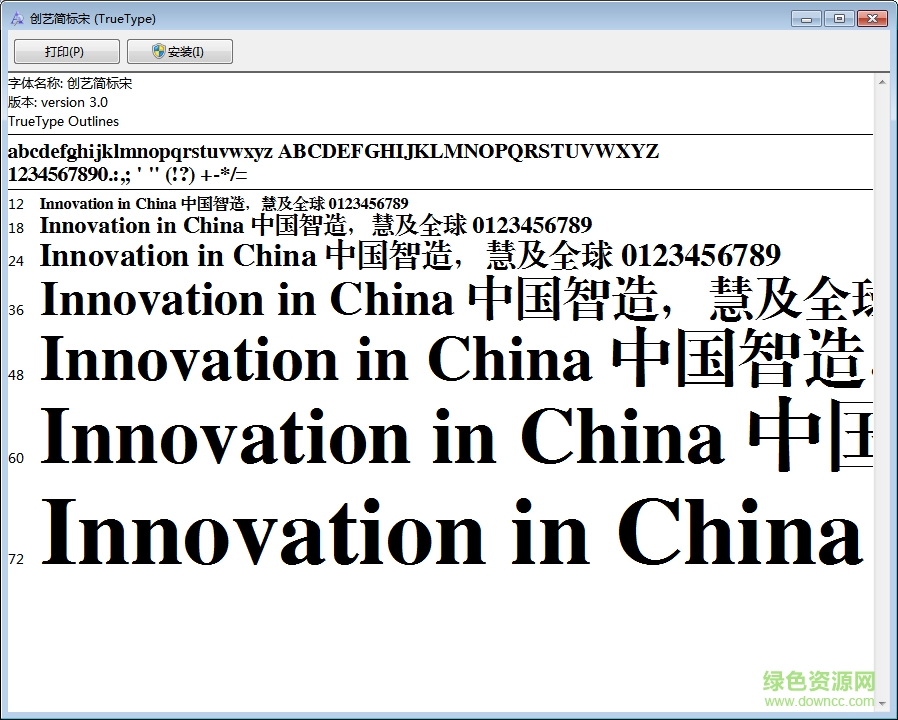
ctbiaosongsj 是什么字體?ctbiaosongsj.ttf字體又叫創(chuàng)藝簡標(biāo)宋,是一款看上去非常正式的宋體字體,該字體粗細(xì)變化得當(dāng),錯落有致,線條舒展自如,韻意深長!
ctbiaosongsj是一款嚴(yán)謹(jǐn)?shù)淖煮w,筆畫粗細(xì)分明,布局嚴(yán)謹(jǐn)且沉穩(wěn),常被用作各類書籍、報紙、雜志等標(biāo)題字。用在廣告設(shè)計方面能夠讓你的廣告字體效果更佳。